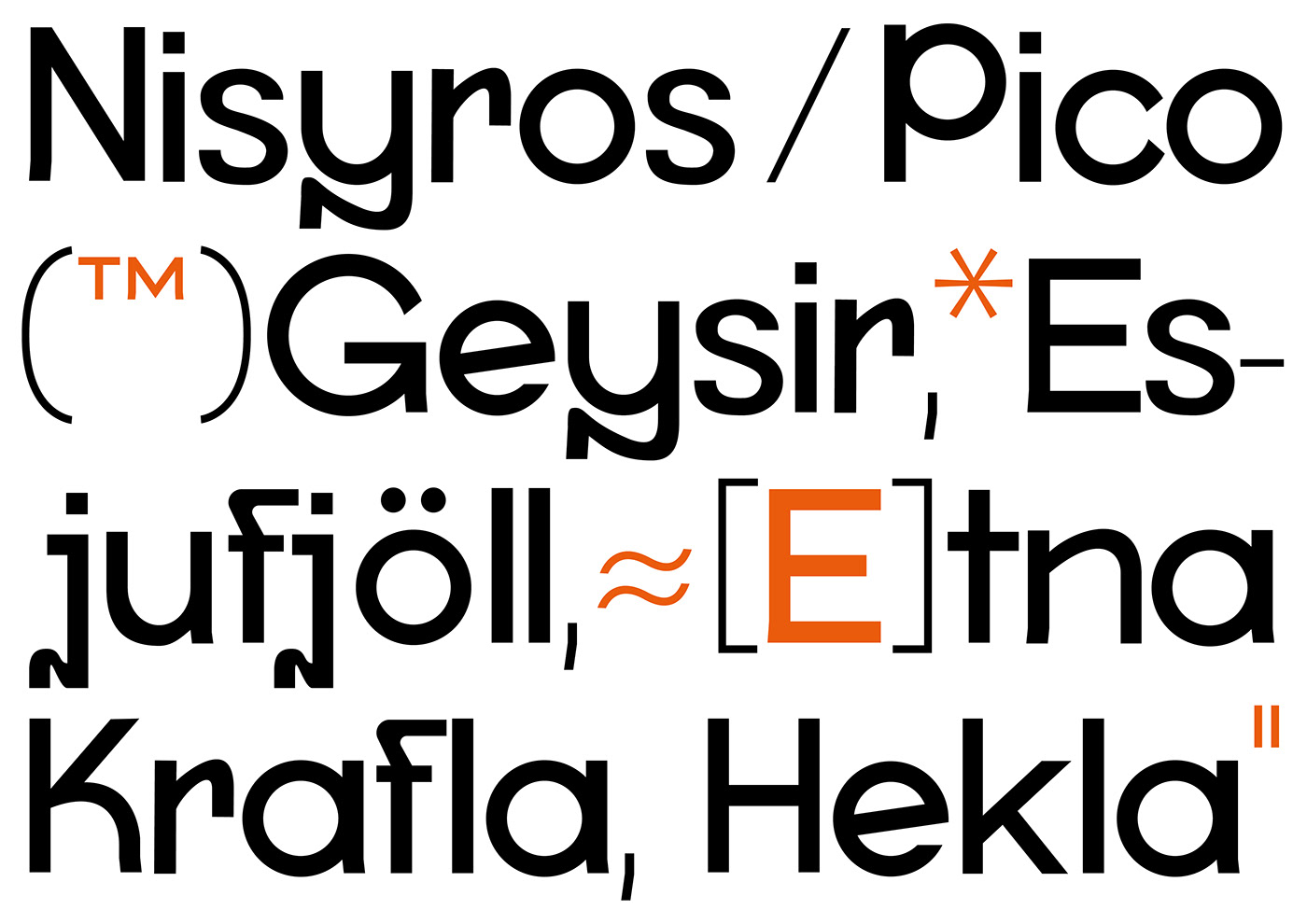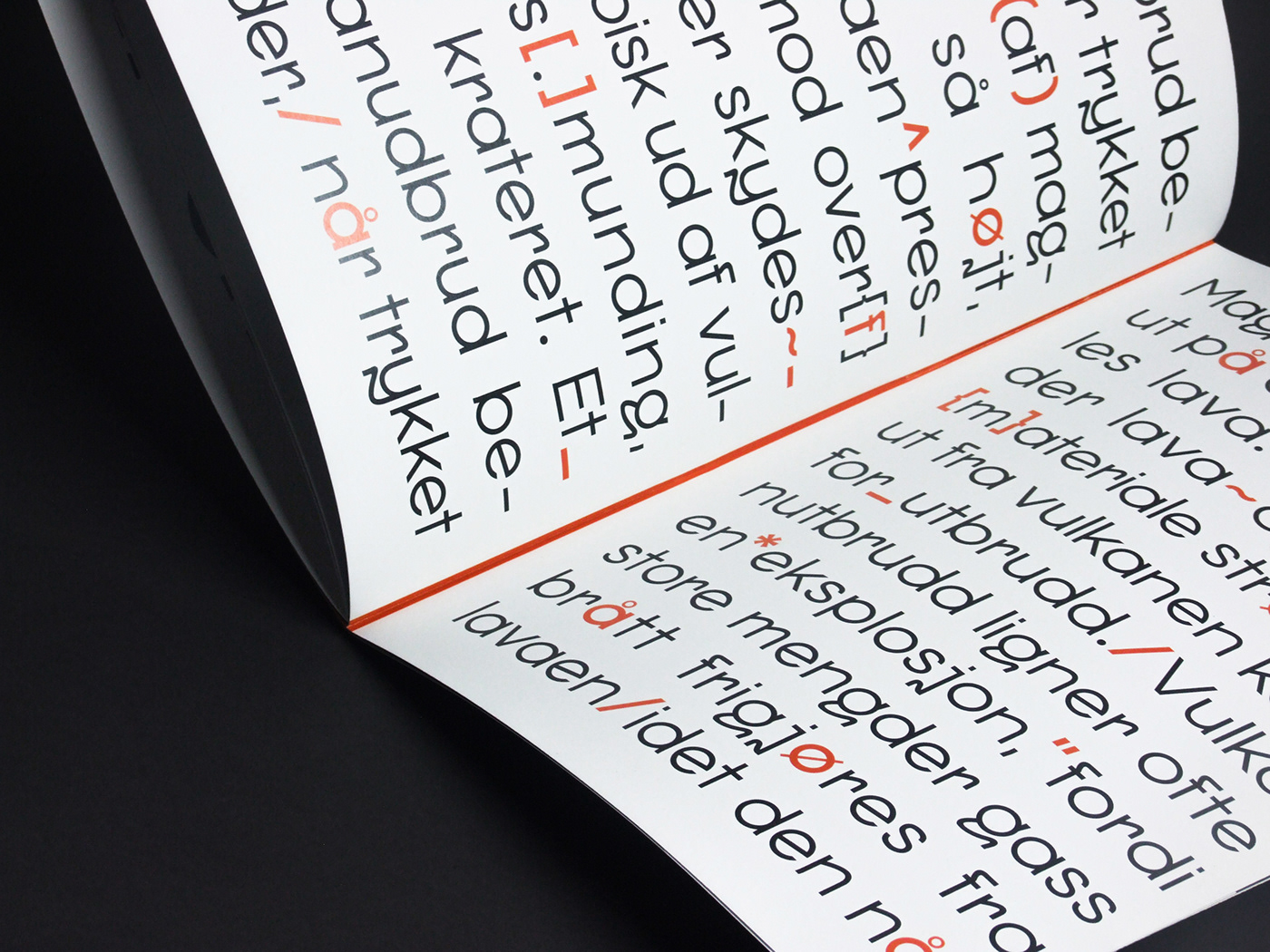
A Jēriko typeface tervezésénél, célom a mai betűtípusokra jellemző formai vonások megragadása volt. A létrejött betűtípus főleg geometrikus formákból áll. Néhány betűben azonban megjelennek organikus vonalak is, ezzel válik jellegzetessé a Jēriko betűcsalád. Három különböző vastagságban és dőlt változatban készült el a font, különleges karakterekkel. A Jēriko font cím feliratokhoz, nagyobb méretű, rövid szövegekhez alkalmas leginkább.
The Jēriko font is based on the formal features of today’s fonts. The complete family of letters consists mainly of geometric shapes. Organic lines also appear in some letters, making the Jēriko font family distinctive. The font was made in three different thicknesses and italics with special characters. The Jericho font is recommended for title captions and short texts.